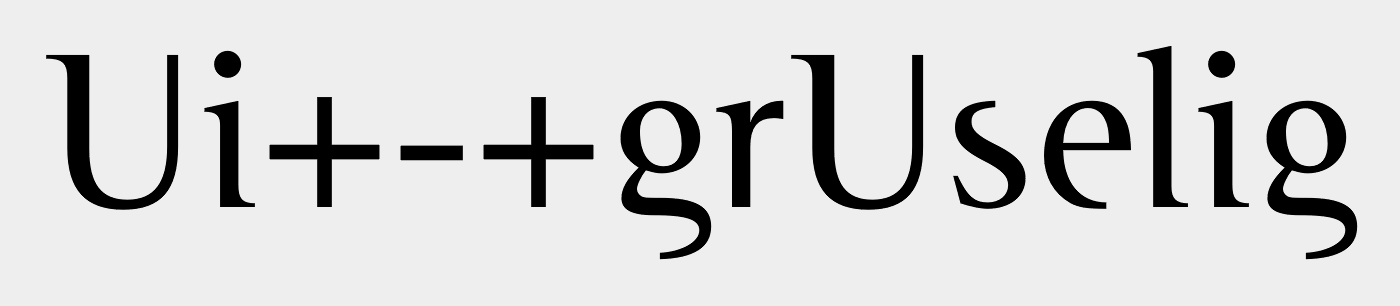
Schrift erkennen an einem U
Sie gruslig aus … die P22 Foxtrot Sans hat formal so ein U.
Cutoff ist relativ nah dran (vertikal gestreckt). Inzwischen glaube ich, dass das U gestreckt oder verlängert wurde*. Eventuell gab es auch mehr Serifen.
*darauf deutet meiner Meinung nach die unsaubere rechte Pixelkante der linken Senkrechten hin. Das U stammt aus einem Logo, welches nur als PNG vorliegt, in keiner besseren Auflösung als der gezeigten. Als Vektoren gibt es nur eine schlecht nachgezeichnete Version, wahrscheinlich auf Grundlage genau dieser PNG-Datei.